今回は、呪文・暗号にぴったりのおすすめフォントをまとめてみました。
ファンタジー物語やミステリー漫画や動画などで、「呪文・暗号」を表現したいシーンなどがありますが、通常の文字より少し変形した文字の方が、より世界観を表現できます。今回ご紹介するのは、ひとクセある一風変わったフォントで、「呪文・暗号」を表現したいシーンで活用できるフォントです。
見ているだけでも楽しめるフォントばかりなので、ぜひ参考にしてみてください。
「呪文・暗号」におすすめの日本語フリーフォント
本記事で紹介しているフォントの一部ですが、このようないい意味でのひとクセがある「呪文・暗号」にぴったりなフォントをご紹介します。
異星の字
異星の字フォントは、「地球外生命体が喋りそうな文字」をテーマに制作されたデザインフォントです。魔法呪文などにもぴったりです。
ぐちゃもじ
ぐちゃもじフォントは、グチャグチャと塗りつぶしたようなユニークなフォントです。
ダイイングメッセージなどのミステリーぽさを表現するにおすすめです。
ich1Q
ich1Q(異地球言語フォント)フォントは、異世界の文字のような読めそうで読めない不思議な文字のフォントです。読めそうで読めないところが、クリーチャーが魔法の呪文などの表現にぴったりなフォントです。
ギシローレーカー
ギシローレーカーフォント、文字同士が横一直線に繋がる仕掛けが施されているデザインフォントです。ヒンディー語・ネパール語(デーヴァナーガリー文字)のように、文字と文字が繋がっているユニークなデザインになっています。
一筆足らず
一筆足らずフォントは、「どこか何か足りてない。でも形はイメージできちゃう。」をテーマにワンストロークで書かれたユニークなフォントです。謎解きなどの暗号メッセージにぴったりなフォントです。
JikiTourai
JikiTourai (磁気到来) フォントは、「UkiyoMoji Fonts」さんによるレトロフューチャーでデジタル感がとってもかっこいいデザインフォントです。
Narehate(なれはて)
Narehate(なれはて)フォントは、ひらがなの成れの果てのように変形させたデザインフォントです。
ひらがなの原型はある程度残されているので、読めなさそうで読めるぐらいまでの変形されているバランス感良い具合が、暗号や呪文ぽさを感じるフォントです。
異形明朝
異形明朝フォントは、源ノ明朝をベースに、生成AIで明朝体のチューニングして生成されたユニークな明朝体フォントです。こちらも読めそうで読めない、そんな絶妙なフォントなので、呪文や暗号っぽさを表現するのにぴったりです。
Electroharmonix
Electroharmonixフォントは、ひらがな・カタカナ・漢字のように見えるけど、本当にはアルファベットになっているフォントです。
セネシオまちっく
セネシオまちっくフォントは、直線と円を組み合わせて作られたデザインフォントです。
古文書崩し字かなフォント
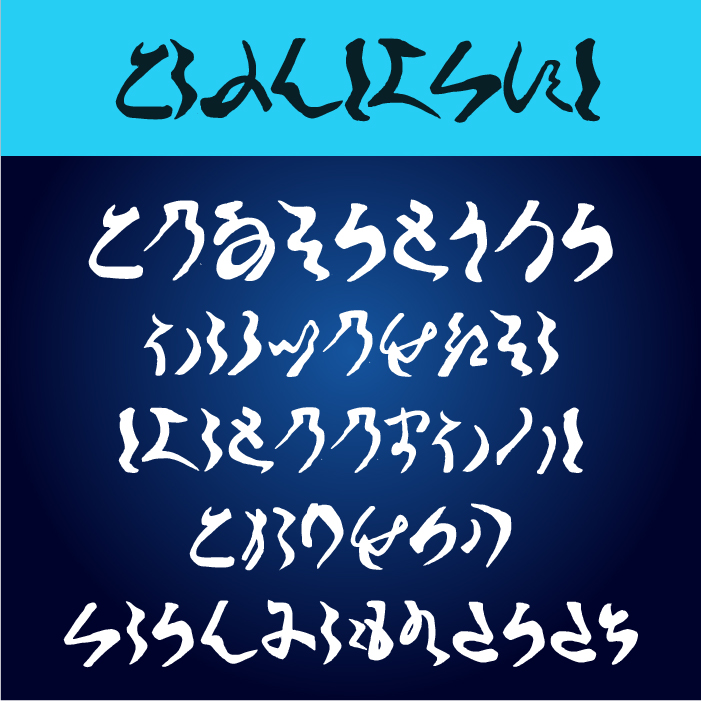
古文書崩し字かなフォントは、実際に古文書の中で使用されているひらがなをベースに制作されたフォントです。
忍者文字
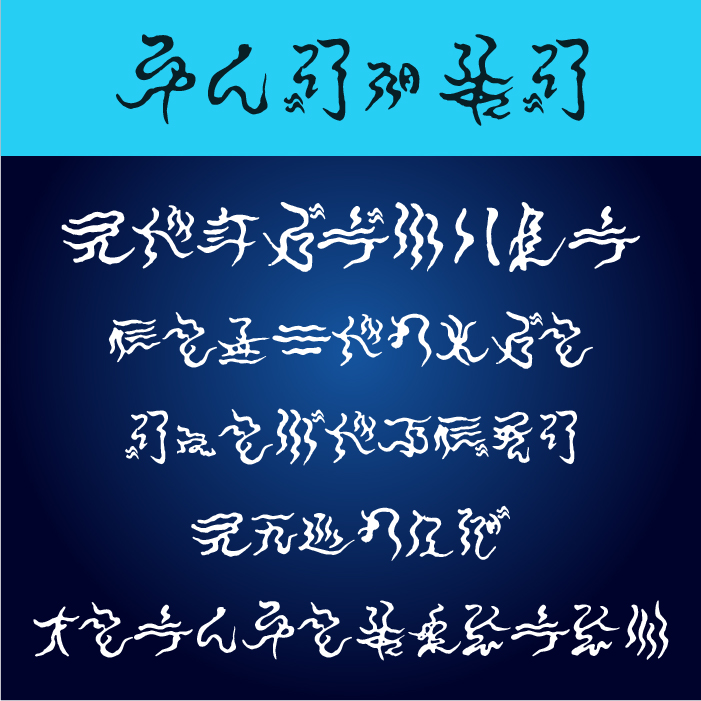
忍者文字フォントは、伊賀忍者で有名な三重県伊賀市の上野商工会議所観光部会が制作した「神代文字」を再現したフォントです。忍者だけが解読できる暗号のようなフォントです。